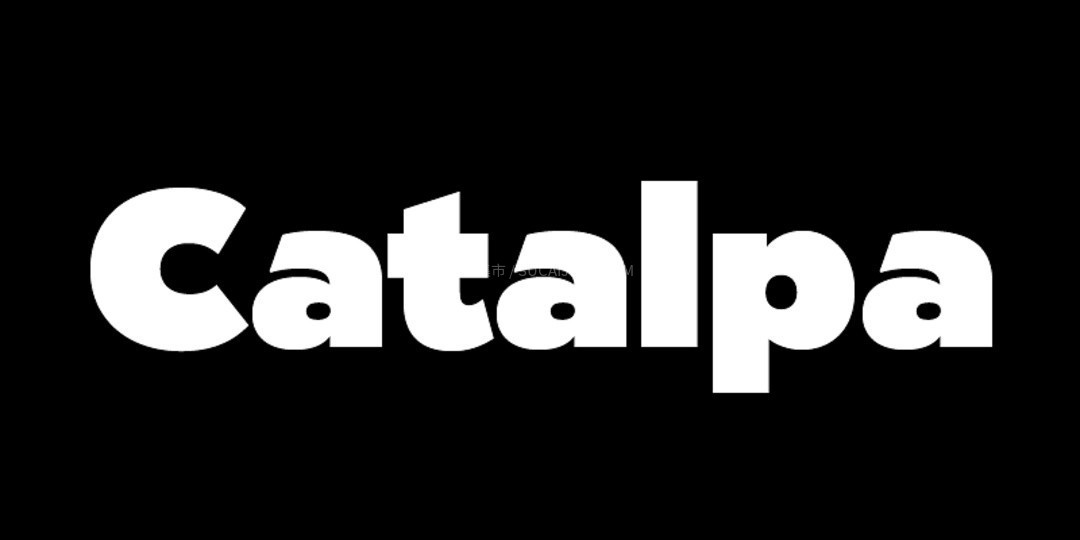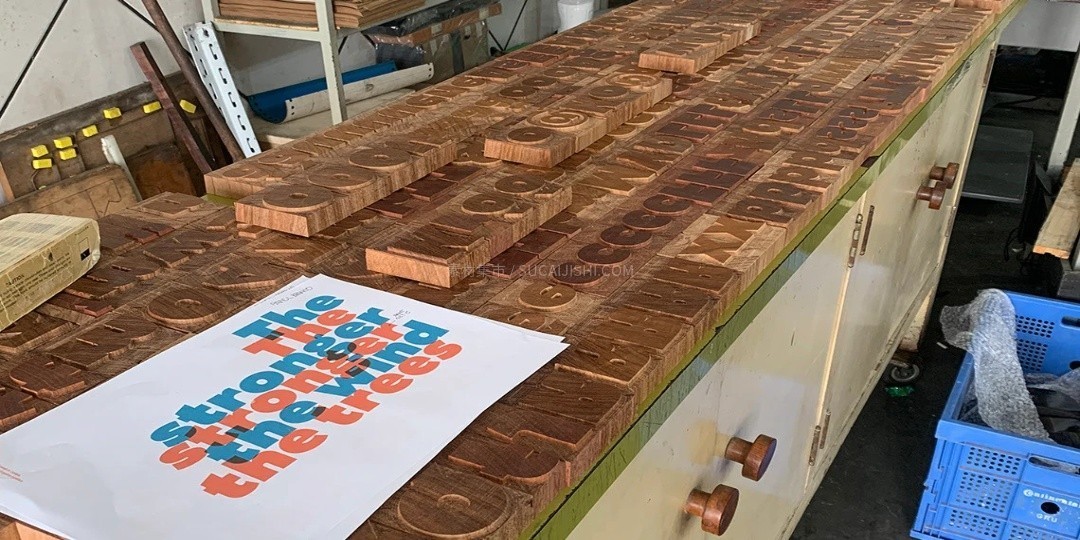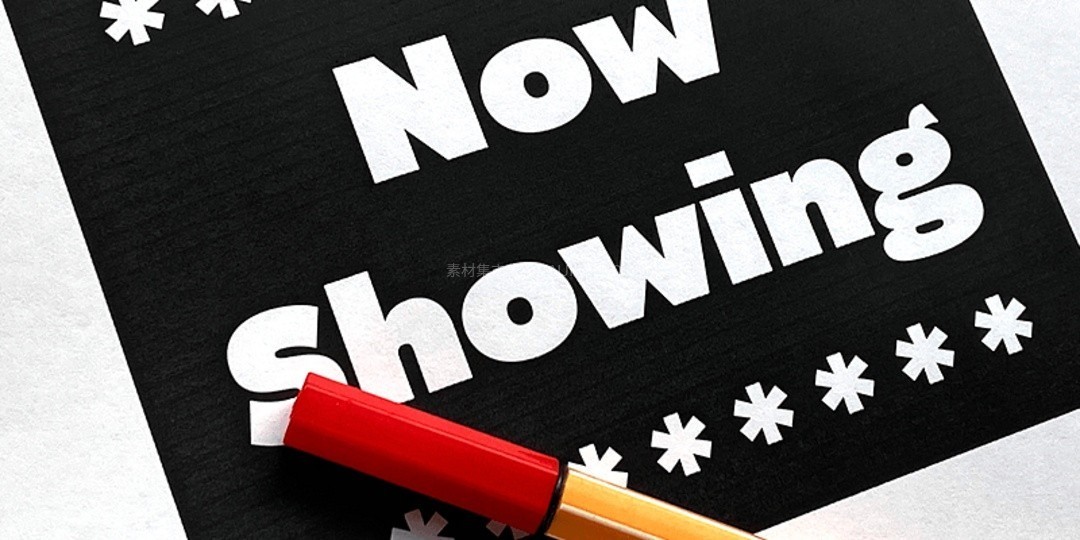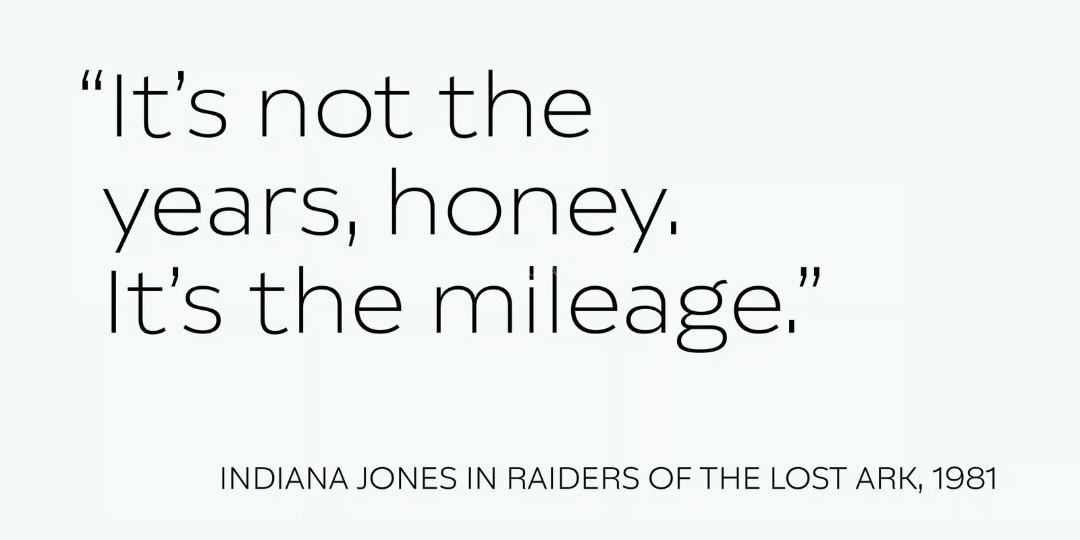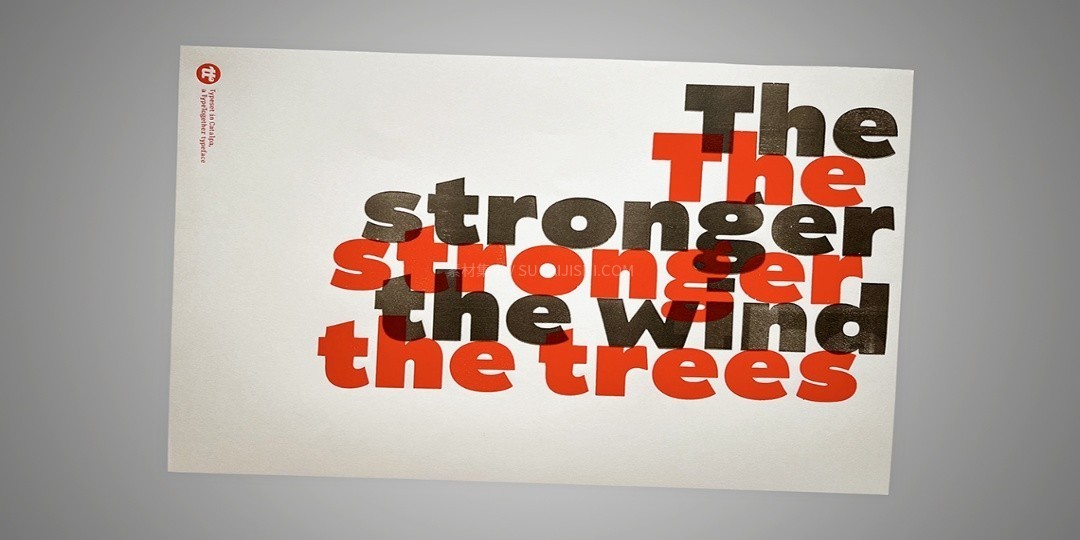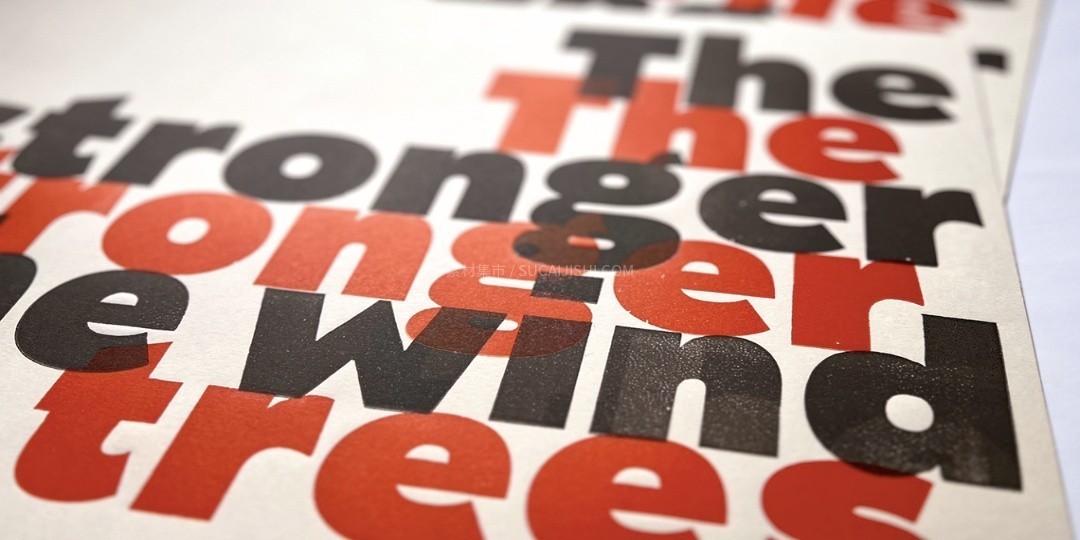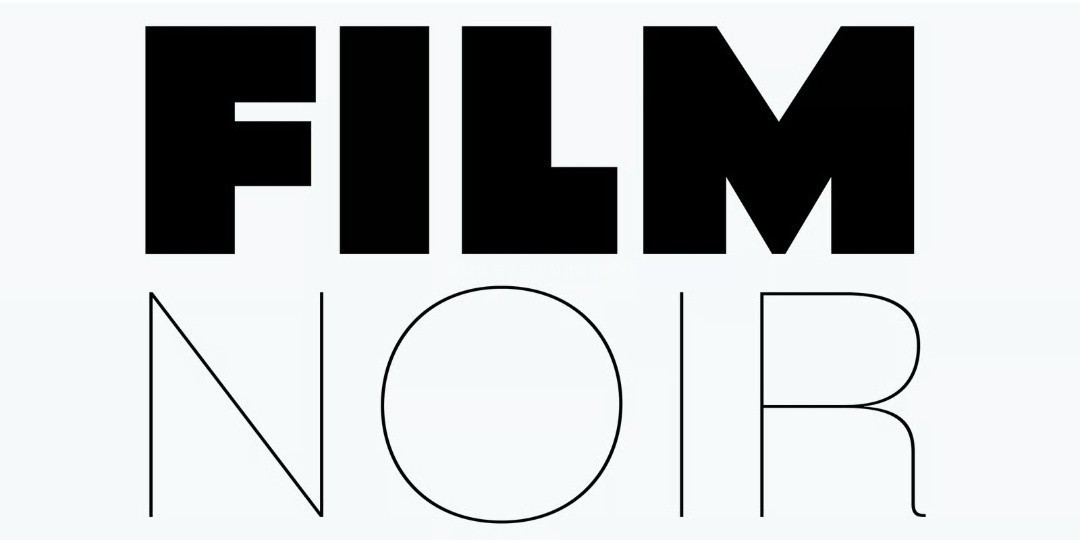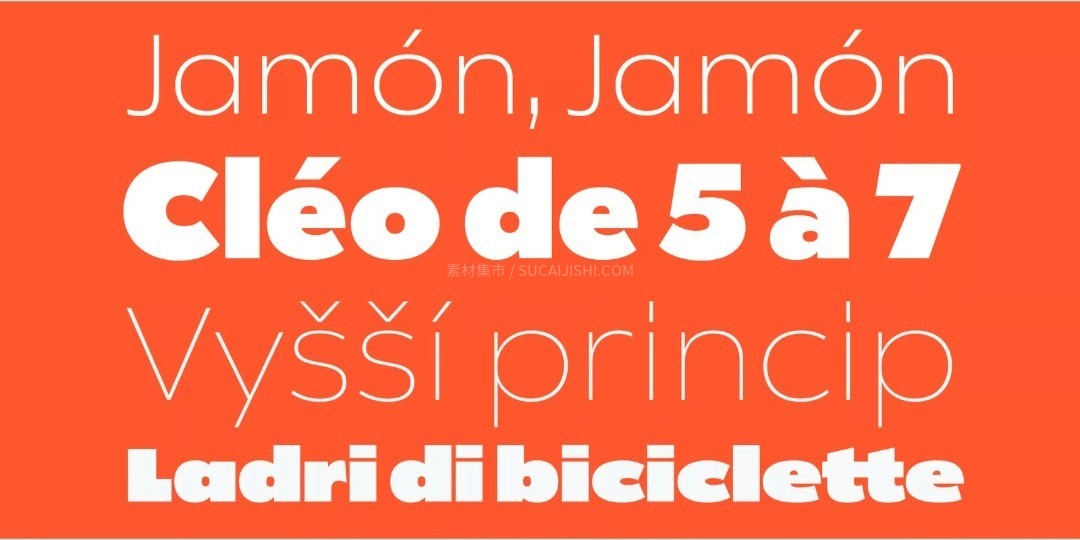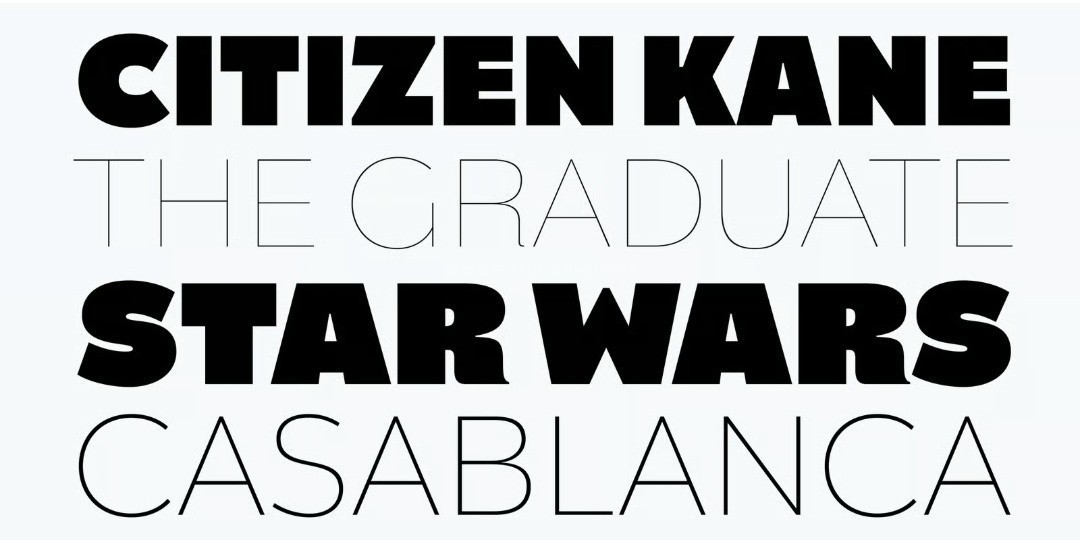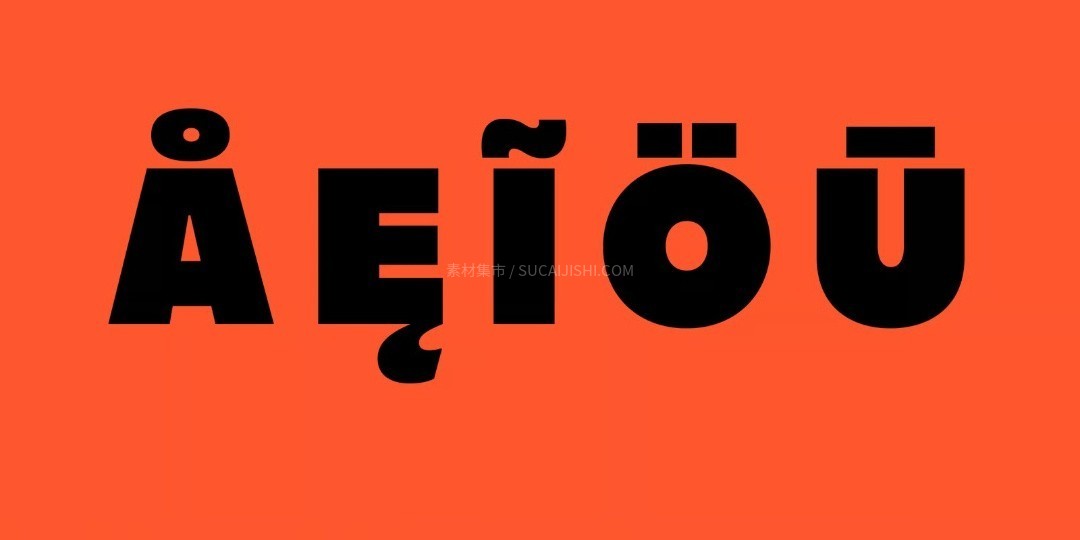
Catalpa 荣获国际大奖的可变字体家族
Catalpa 是一款由 TypeTogether 团队的 José Scaglione 与 Veronika Burian 联合设计的高级展示型字体。该字体灵感源自传统木刻印版,并荣获 2020 年 Selección Clap 最佳标题字体设计及 2021 年 Indigo 金奖。为满足大尺寸标题排版的严苛需求,Catalpa 采取了极端的字重分布策略,摒弃了常规中等字重,提供 4 种极细字重(Hairline 至 Light)与 4 种极粗字重(Extrabold 至 Extrablack)。通过套装内包含的两款可变字体文件,设计师可在极细与极粗两端进行高精度的无缝微调。在设计细节上,Catalpa 巧妙融合了几何结构与鲜明的字形特征(如反色对比的“S”及棱角分明的特定字符),能够在各种数字屏幕与印刷基材上呈现出卓越的视觉冲击力与辨识度。